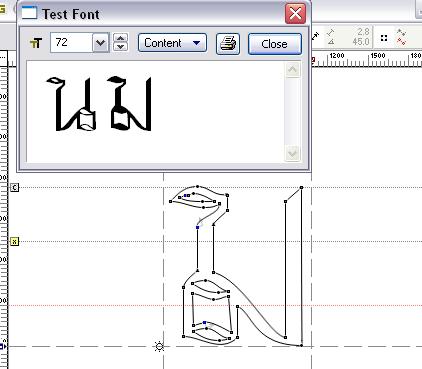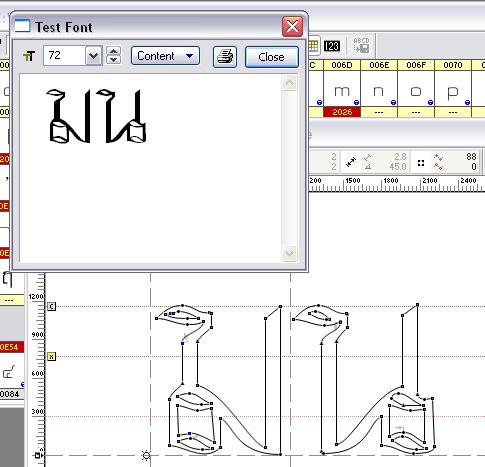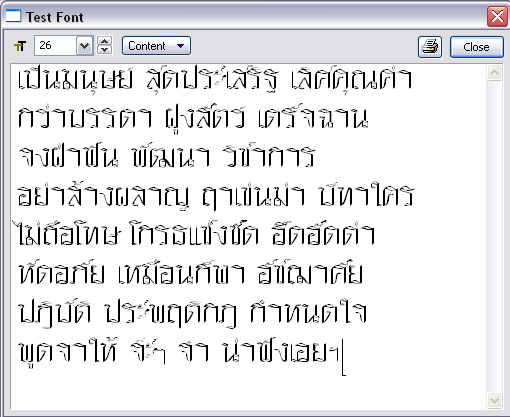
ลองทำฟอนต์ครับ
รบกวนถามครับ   มีปัญหาดังนี้ครับ
ตัว ม.ม้า  เวลาtest แล้วมันทึบหมดเลยครับ  การทำก็ทำแบบน.หนู(ผมทำน.หนูก่อน ไม่มีปัญหาอะไร)
แต่ถ้าก๊อบ น.หนู หรือ ตัวอักษรอื่นๆ มาวางข้างๆ  แล้ว test    มันกลับโปร่งแฮะ :06:
พอลบ น.หนู ออกไป  เหลือ ม.ม้าเพียงตัวเดียว
มันก็ทึบอึก
ผมลองเอา น.หนู  วางในช่อง ม ม้า    ตัว น .หนู ก็โปร่งตามปกติ
แต่
ผมก็ลองเอา ม.ม้า  ไปไว้ที่ช่อง  ตัวอักษร  น.หนู ก็ทึบเหมือนเดิมครับ ( ถ้าม.อยู่เดี่ยวๆ)
ผมจะทำให้ ม ม้า โปร่ง ได้อย่างไรครับ ช่วยหน่อยนะครับ
ไม่มีฟ้อนแลบแฮะ
จำได้ลางๆว่า ปัญหาอย่างนี้เกิดจากเวคเตอร์มันวนกันคนละทาง ทำให้หัวมอม้าไม่โปร่ง
ต้องคลิกขวา แล้วสั่งอะไรสักอย่างให้มันวนกลับด้านน่ะครับ
วิธีแก้ก็ตามลุงหนวดเลยครับ
- Ctrl+คลิกตรงพื้นที่ที่มีปัญหาเพื่อเลือก มันจะเป็นขอบสีแดง
- คลิกขวาตรงเส้นแดง แล้วหา Reverse Contour
ป.ล.กด Ctrl+Shift+P เพื่อให้มัน Fill Outlines จะเจ๋งมาก ดำเป็นดำ ขาวเป็นขาว
งานออกมา แล้ววววววววววว  ยังไม่สมบูรณ์เท่าไร
เ   ่    บ๊าง  บาง
ส ล  ไม่สวย
พวกสระบน ไม้โท สวยอยู่ตัวเดียว นอกนั้ บางและมองยาก
ไม้ยมก กับ ฯ บ๊าง บาง
แยก ท กับ ฑ ไม่ออกแฮะ
ฏ ปฏัก หางสั้นไปนิดนึงนะครับ